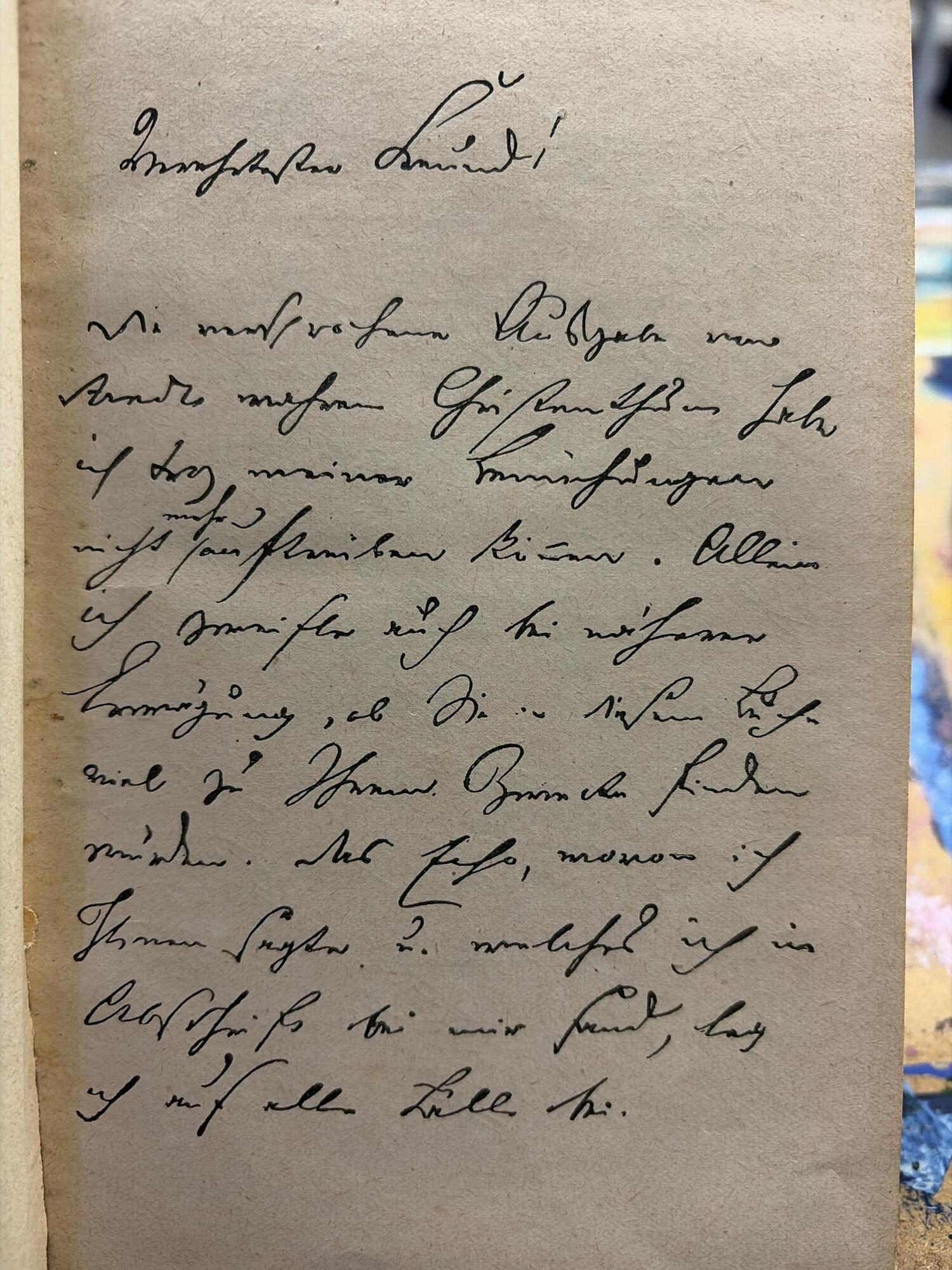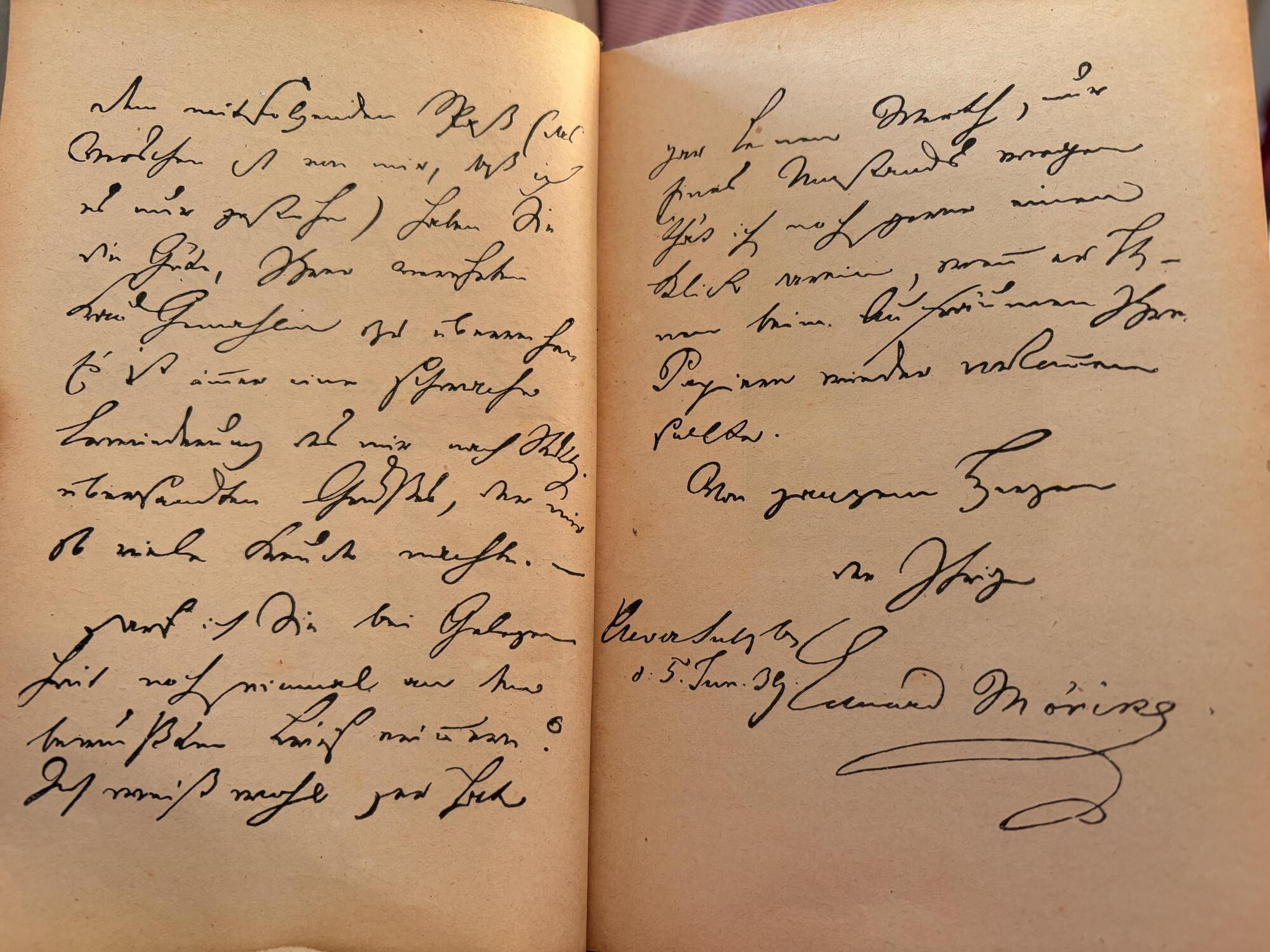
Handschriftlicher Text aus einem Buch von Eduard Mörike
Ich habe aus einer Bücherzelle das Buch Eduard Mörikes sämtliche Werke in sechs Teilen mitgenommen, es ist der erste Band. Herausgegeben wurde es von Rudolf Kraus im Hesse & Becker Verlag, Leipzig.
In dem Buch habe ich drei Seiten in Kurrentschrift gefunden, kann aber leider bis auf Eduard Mörike am Ende und dem Datum fast nichts lesen. Seit Stunden sitze ich jetzt an dem Text und hoffe, dass mir hier jemand weiterhelfen kann.
Ein eigenhändig von Mörike geschriebener Brief in einem Bücherzellenzufallsfund? Das wäre eine Entdeckung.
Die Handschrift ist nicht die sorgfältigste, die Seiten 2 und 3 sind spontan nur Lückentext, aber Seite 1 ist einigermaßen zusammenhängend (bei größerer Vertrautheit mit der Handschrift ergäbe sich vielleicht die eine oder andere Korrektur, aber wir bereiten ja keine wissenschaftliche Edition vor):
Verehrtester Freund!
Die versprochene Ausgabe von Arndts wahrem Christenthum habe ich trotz meiner Bemühungen nicht mehr auftreiben können. Allein ich zweifle auch bei näherer Erwägung, ob Sie in diesem Buche viel zu Ihrem Zwecke finden würden. Das E[ ], wovon ich Ihnen sagte und welches ich in Abschrift bei mir fand, leg ich auf alle Fälle bei.
Unterzeichnet: Von ganzem Herzen der Ihrige ... Cleversulzbach d: 5. Jun. [18]39
Danke für die Hilfe und es ist leider nur ein als Schreibprobe gedruckter Brief von Mörike. Mich hat trotzdem dessen Inhalt interessiert.
Ich habe gerade mal online geschaut und tatsächlich eine elektronische Version einiger Bände der Mörike-Gesamtausgabe gefunden. Band 13 enthält die Transkription des Briefes. Zu meiner Überraschung genügt unsere Version von Seite 1 editorischen Standards, zu ergänzen ist nur "Echo" (es war mal wieder die einfachste Lesart …). Die Seiten 2 und 3, die bei mir spontan nur Lückentext waren, lauten:
Den mitfolgenden Spaß (das Verschen ist von mir, daß ich es nur gestehe) haben Sie die Güte, Ihrer verehrten Frau Gemahlin zu überreichen. Es ist immer eine schwache Erwiederung des mir nach Stuttgart übersandten Grußes, der mir so viele Freude machte. — Darf ich Sie bei Gelegenheit noch einmal an den bewußten Brief erinnern? Ich weiß wohl, er hat gar keinen Werth, nur Eines Umstands wegen thät ich noch gerne einen Blick darein, wenn er Ihnen beim Aufräumen Ihrer Papiere wieder vorkommen sollte.
Der Brief ist an Friedrich Notter gerichtet.